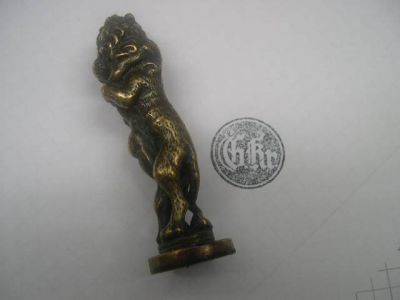
in Anlehnung an das inzwischen ein wenig in Vergessenheit geratenene Handschriften Thema würde mich einmal interessieren, wie es so mit Unterschriften aussieht: Groß oder klein? Eckig oder rund? Vornamen abgekürzt oder nicht? Mit Kugelschreiber/Füllfederhalter oder doch mit etwas anderem? Alles Dinge die bei Unterschriften verschiedener Menschen sehr unterschiedlich sind...
Nun, was ist am besten? Kann man bei solchen Dingen überhaupt zwischen gut und schlecht unterscheiden?
Hast Du keine Bedenken, Deine Unterschrift frei zugänglich ins Netz zu stellen? Sind ja nicht nur Typographen und andere nette Leute unterwegs.
... würd ich auch nicht machen. Besser wieder löschen, das Bild. Ansonsten: Dokumentenecht unterschreiben.
Naja, der Mann von Welt nutzt eh meist seine persönliche Petschaft.
Das hat doch viel mehr Stil... :)
Meine stammt, nebenher erwähnt, aus den Beständen Gerhard Roßbachs von 1920, zeigt den Kampf Samsons mit dem Löwen.Die Siegelplatte mit meinen Initialen GKr habe ich nachträglich anlöten lassen.
GKr
Hm ok, ich hab es wieder rausgenommen, aber was meinst du mit "dokumentenecht Unterschreiben" ???